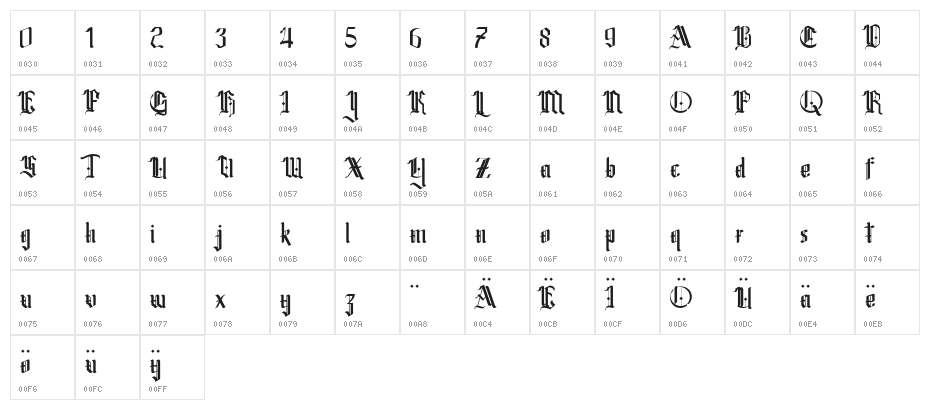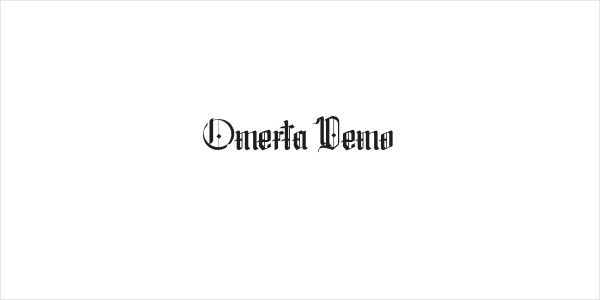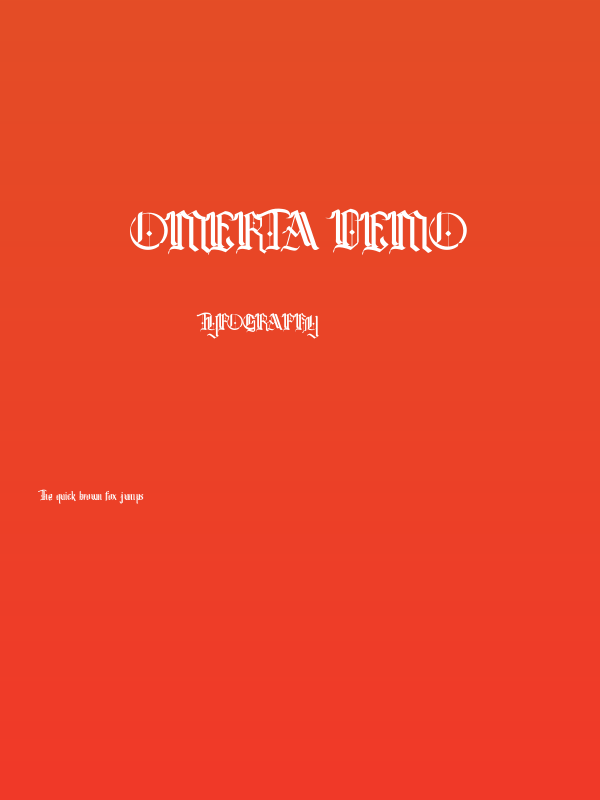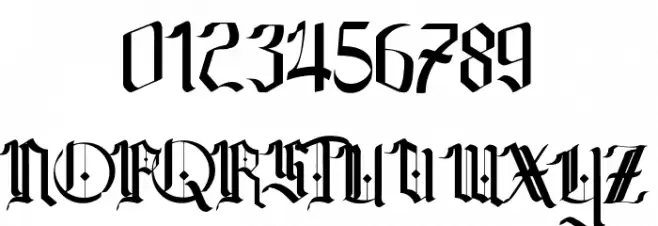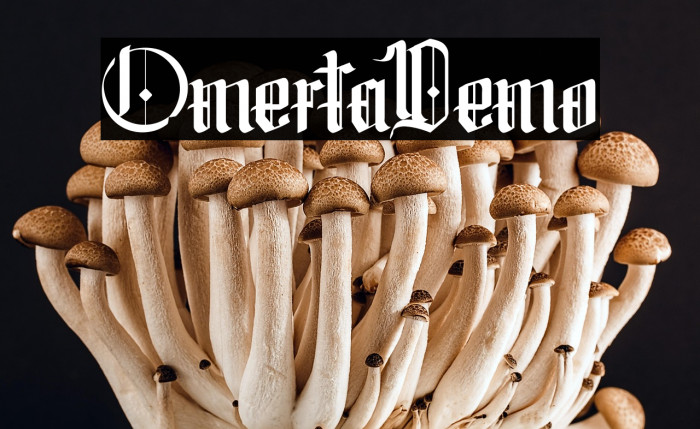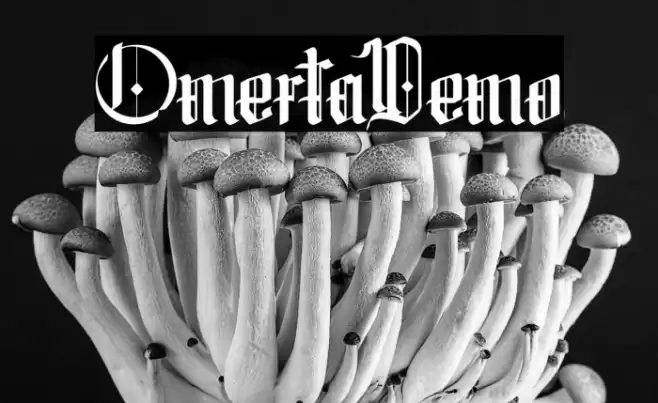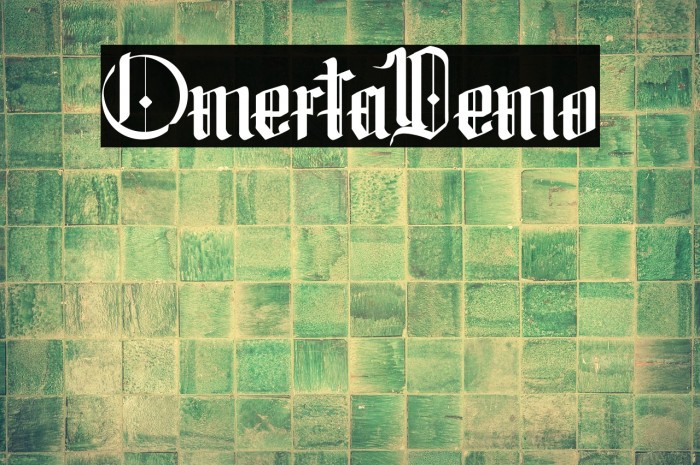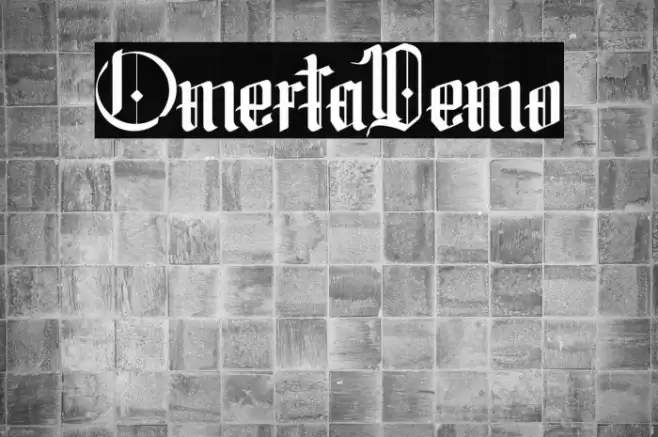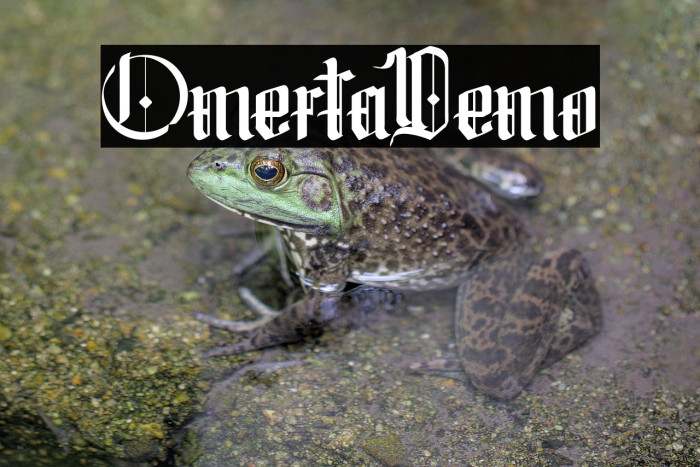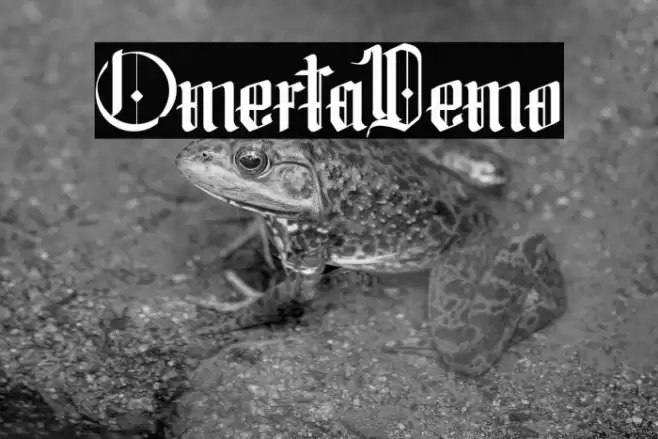
Omerta-Demo Font
✎ Gothic
| Estilo general | Gothic, Traditional |
| Caso de uso | Headlines, Logos, Decorative text |
| Proyectos propuestos | Ideal for projects that require a historical or Gothic touch, such as medieval-themed designs, book covers, posters, or branding for niche markets. |